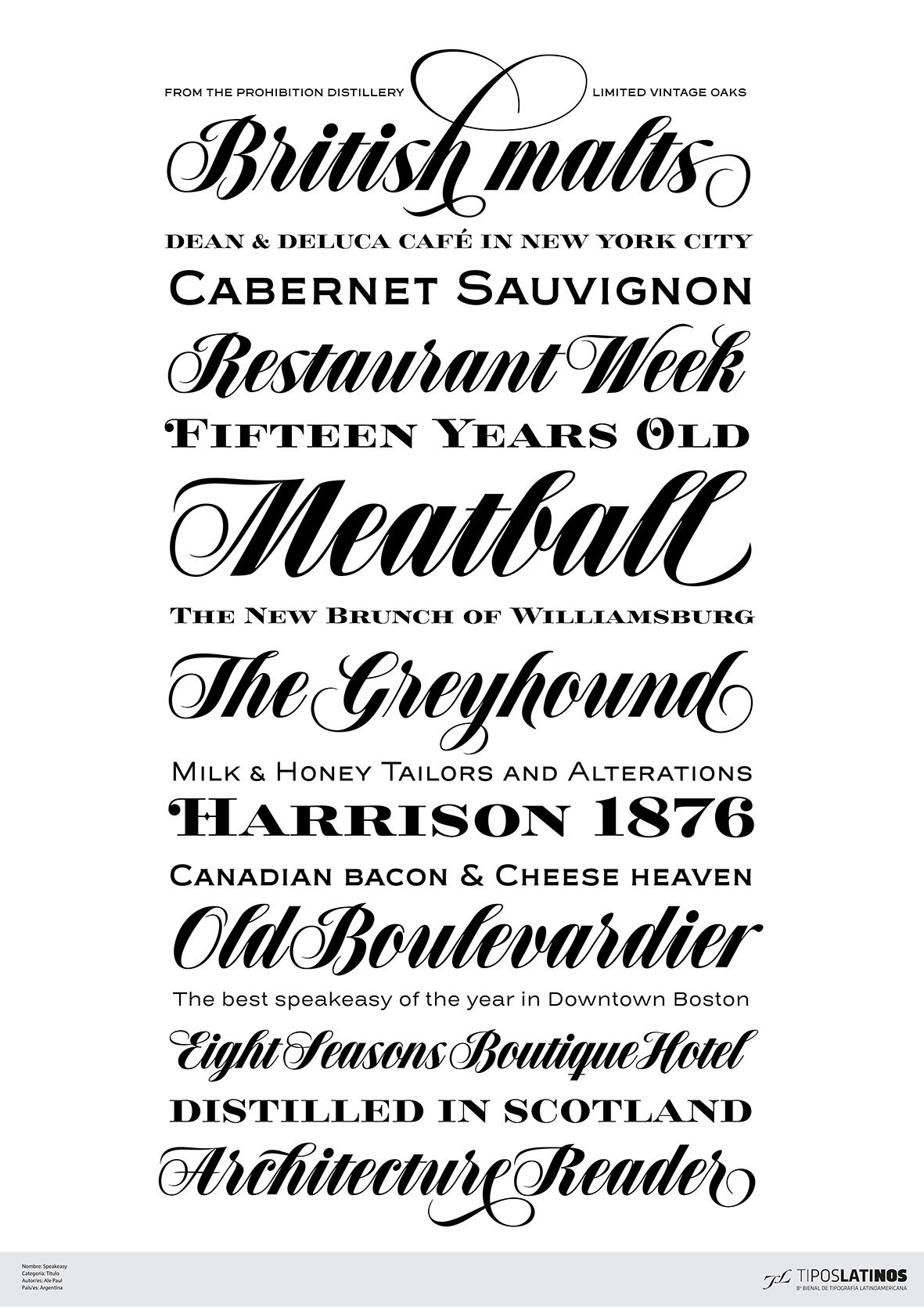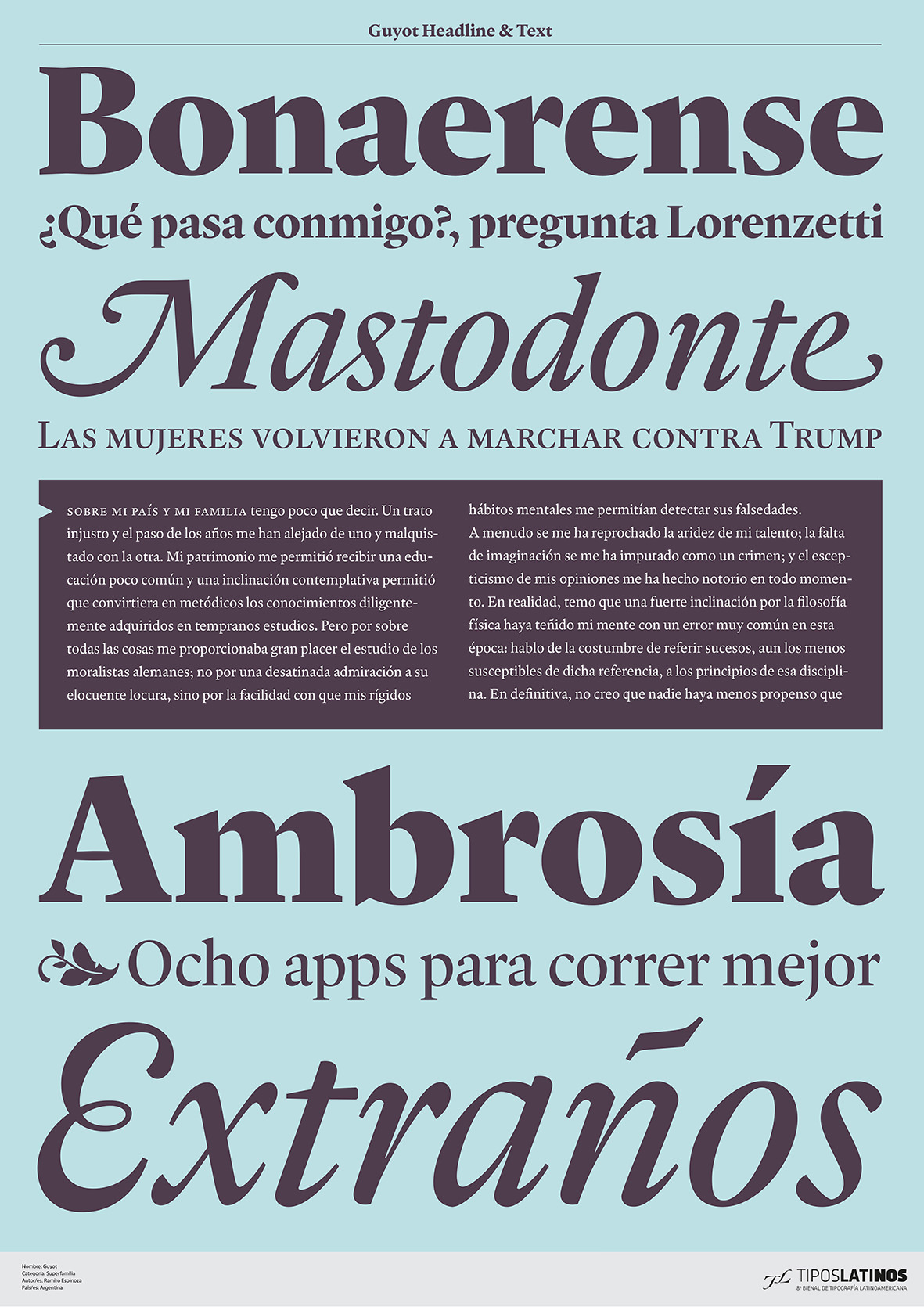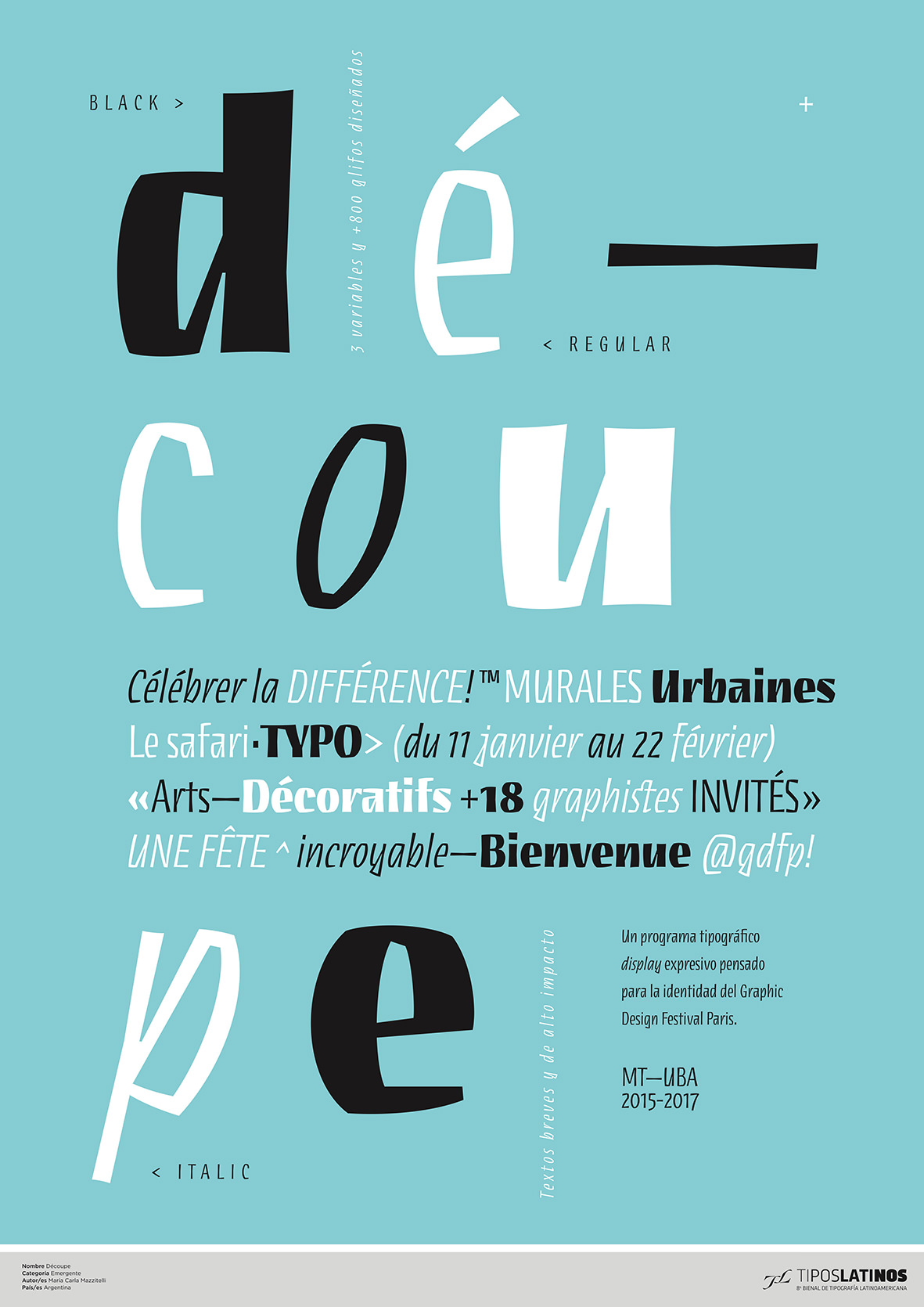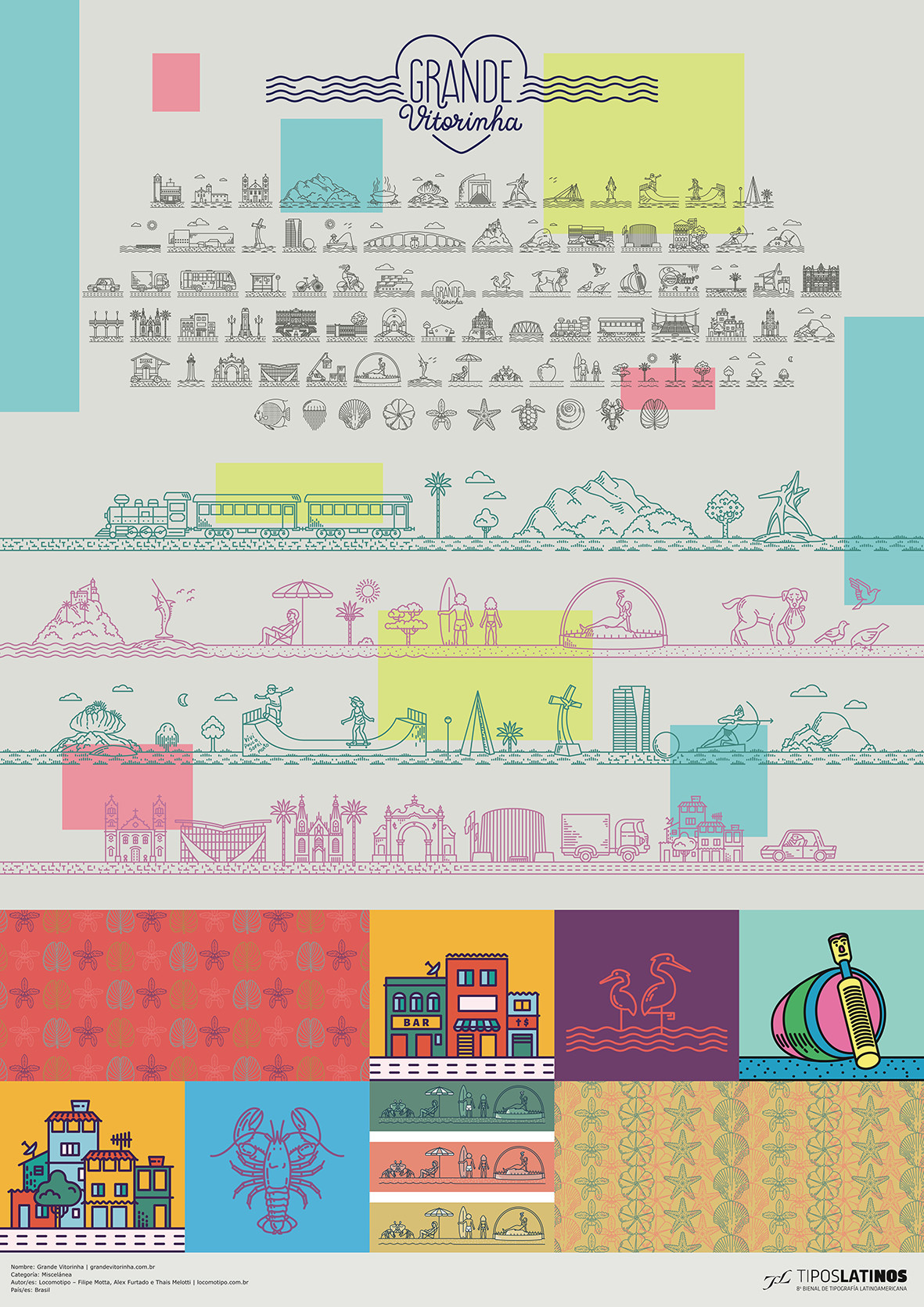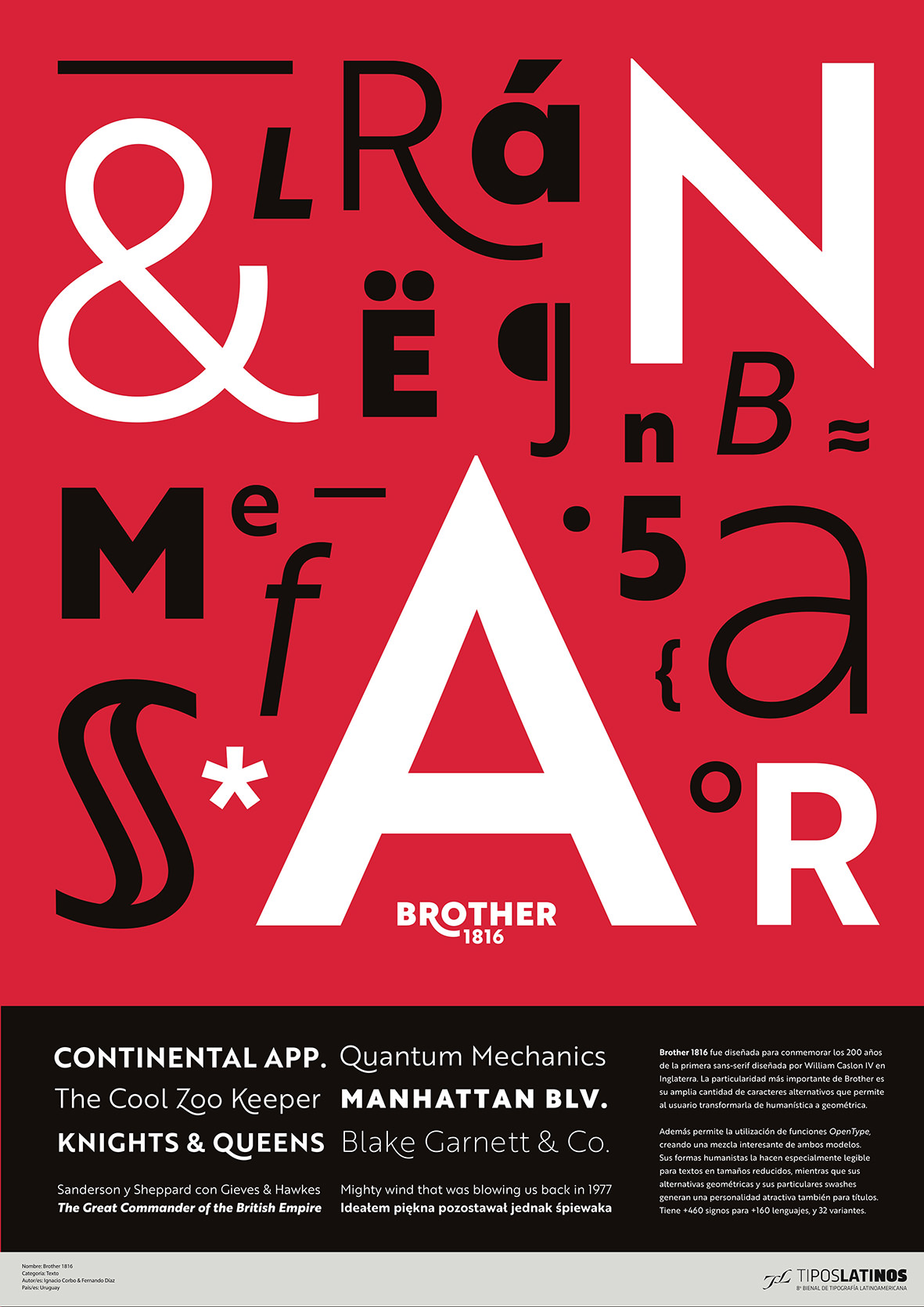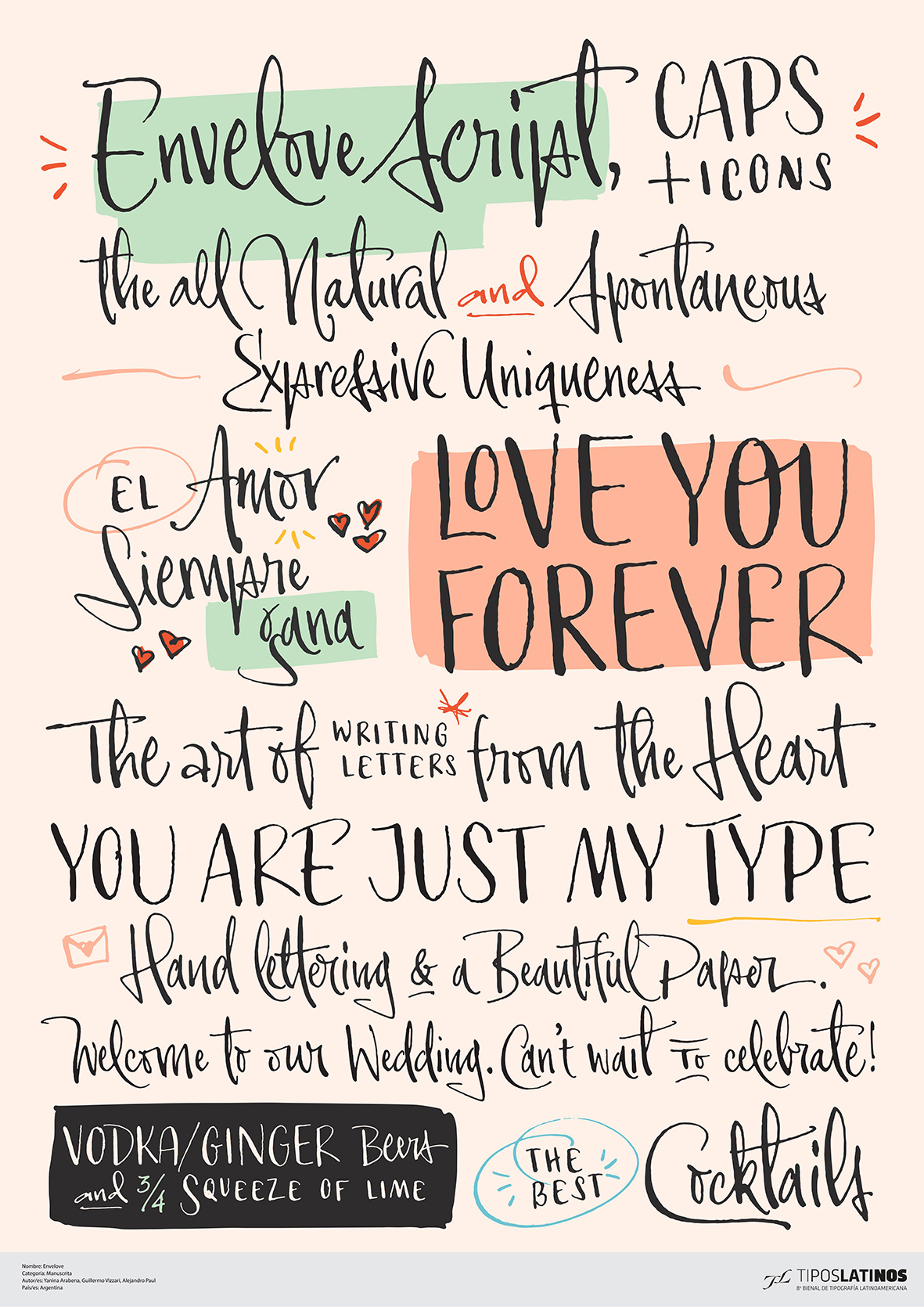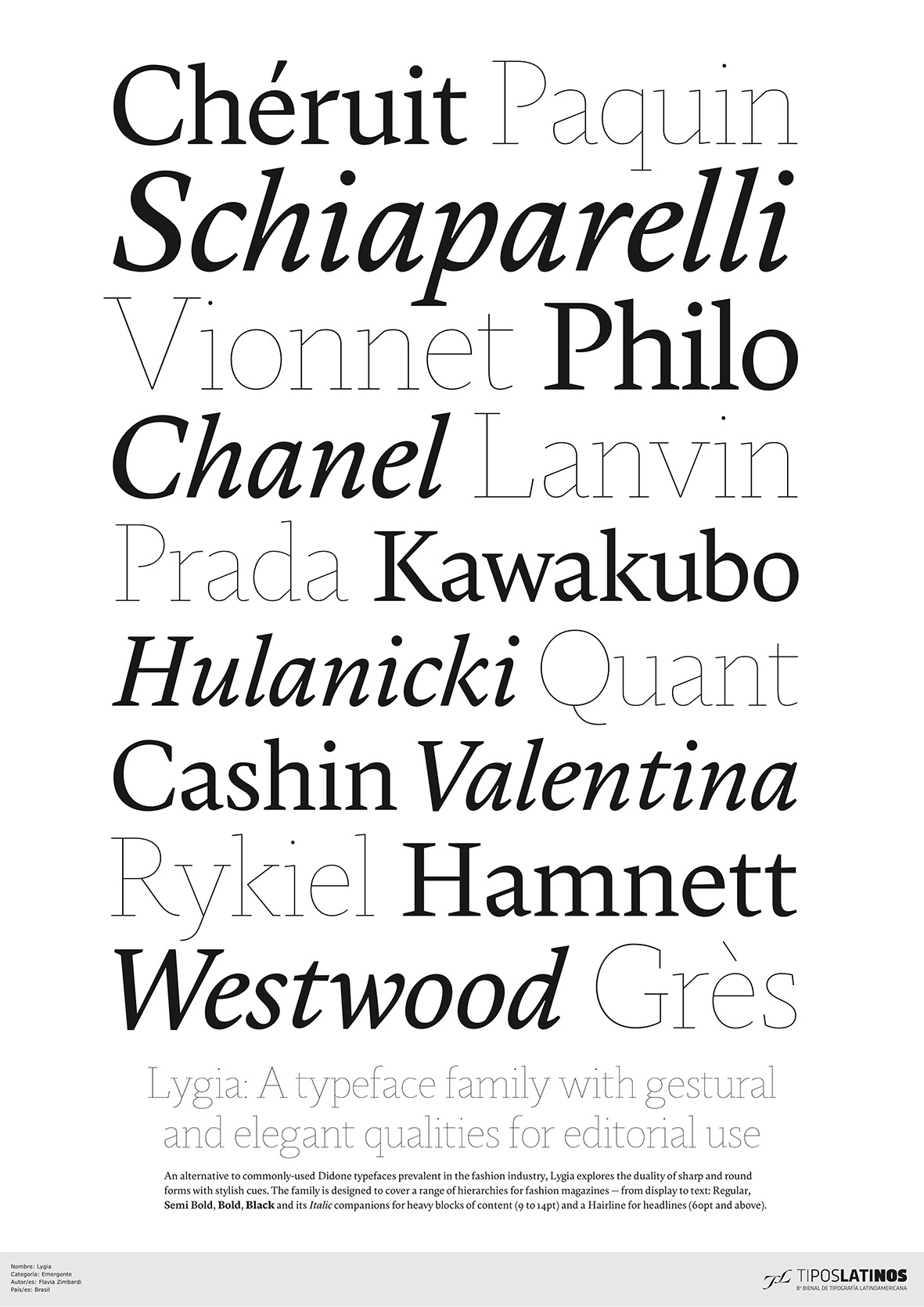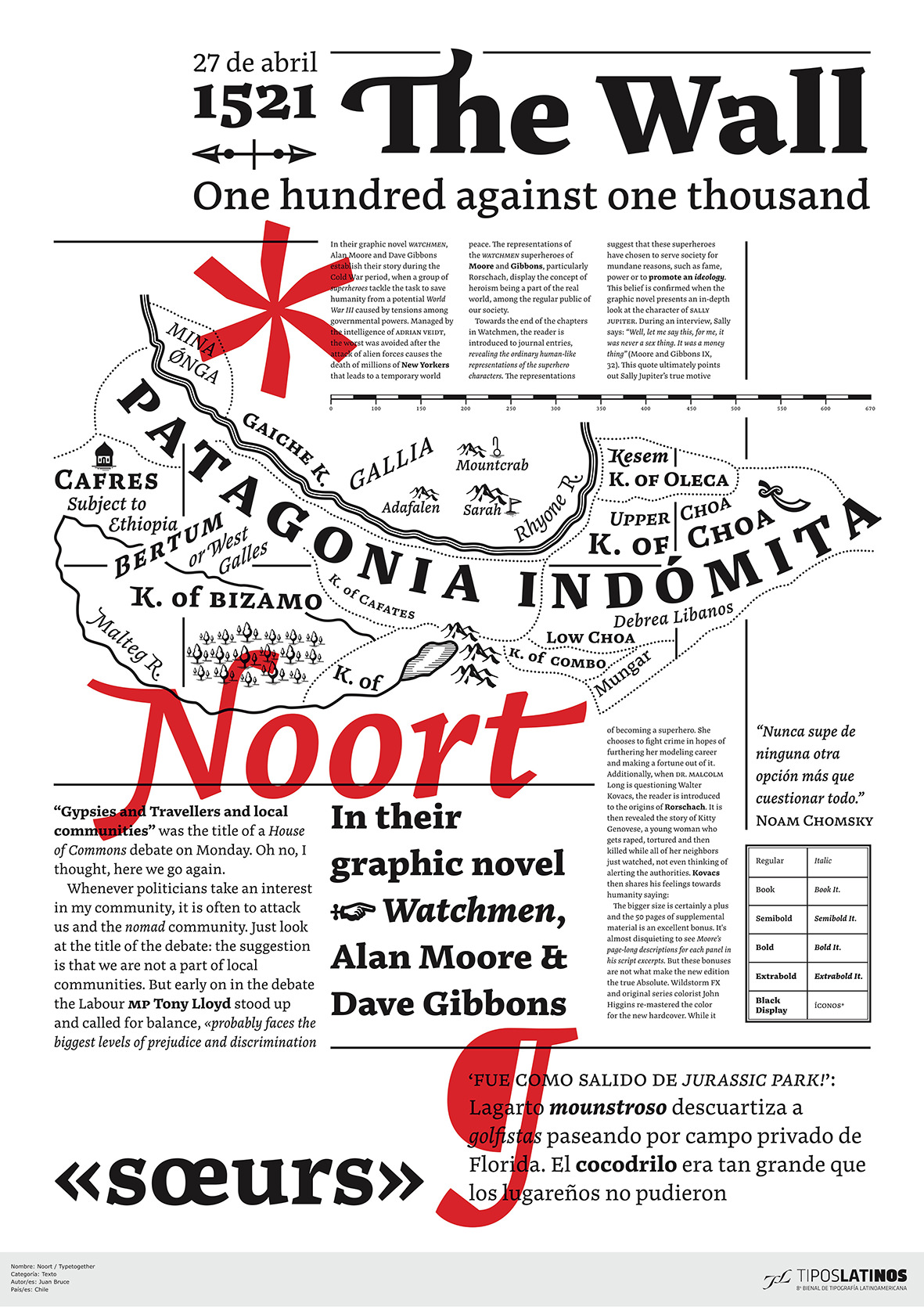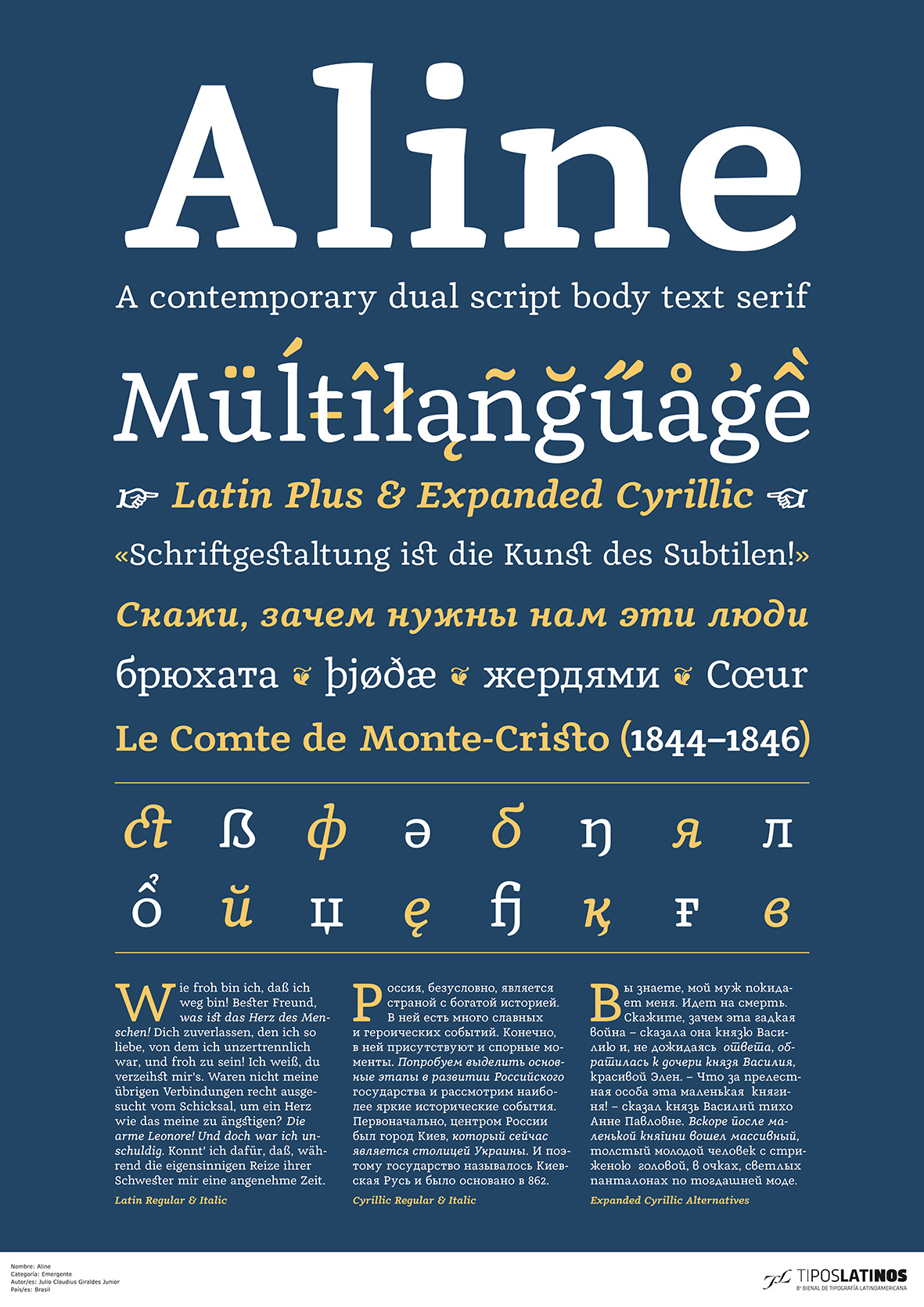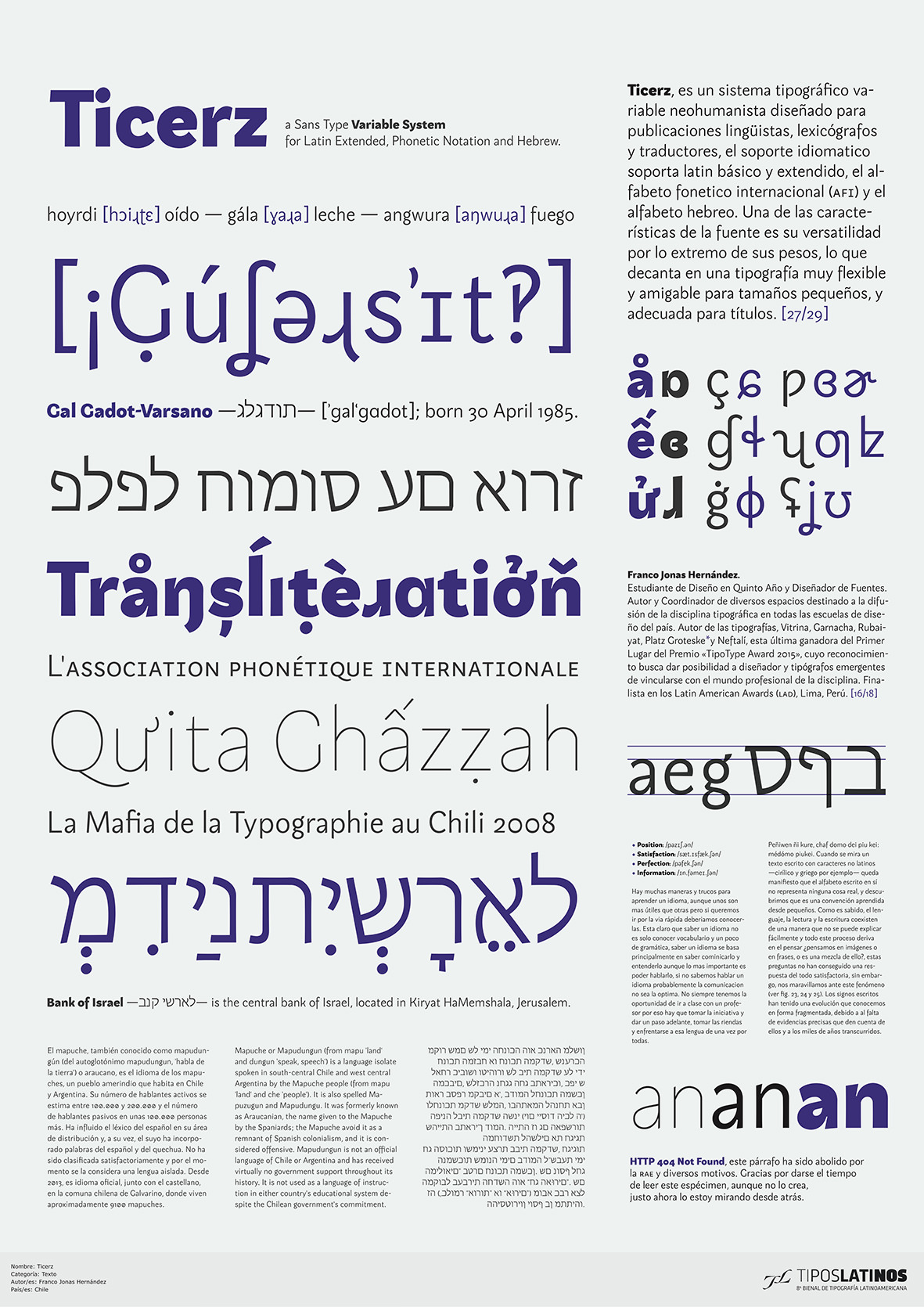
2018 Resultados
Entre los días 21 y 24 de marzo, en la ciudad de Bogotá, Colombia, el Jurado de la Octava Bienal de Tipografía Latinoamericana se reunió para evaluar los 444 proyectos que dieron respuesta a la convocatoria pública. Al final de la cuarta jornada, y después de deliberar libremente, los miembros del jurado seleccionaron 74 proyectos que conforman la muestra de la Octava Bienal Tipos Latinos, otorgando esta vez un total de 4 Constancias de Excelencia.
Tipografías destinadas a la composción de textos en condiciones de lectura prolongada, con énfasis en la legibilidad y la confortabilidad del usuario lector.
Tipografías destinadas a jerarquizar y/o a conferir identidad a la información que la circunda. Su uso especial está orientado a textos breves y en cuerpos grandes.
Tipografías con foco en la experimentación y el proceso de diseño, en las que puede contemplarse o no la legibilidad, dado que la búsqueda y la experimentación resultan
más importantes.
Tipografías integradas por signos no alfabéticos –incluidos pictogramas e íconos– que, organizados en temáticas específicas y diversas, pueden ser usadas de manera autónoma o en combinación con fuentes integradas por signos alfabéticos.
Tipografías que simulan la rotulación manual o ejemplos de rotulación integrada en propuestas de identidad.
Trabajos realizados por estudiantes que están cursando o que hayan terminado sus estudios y/o no profesionales que nunca hayan publicado una familia tipográfica de manera comercial.
Sistemas tipográficos que contienen más de una «forma» o «estilo». Familias seriales, familias con más de un eje de interpolación, familias que contemplen más de un sistema de escritura, etc.
El Jurado decidió otorgar cuatro Menciones de Excelencia: Atahualpa, Otta, Skill, Thesaurus